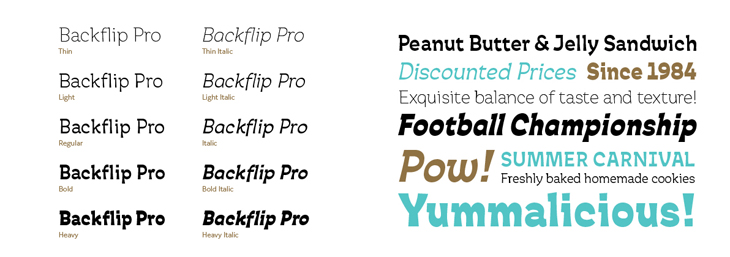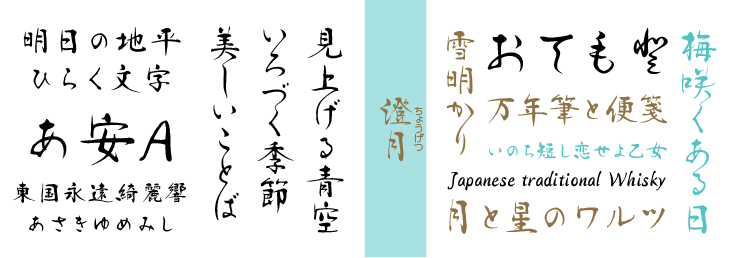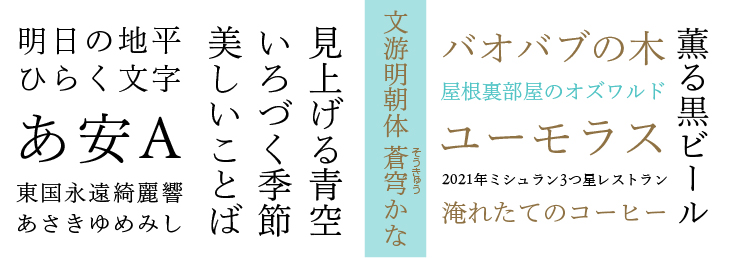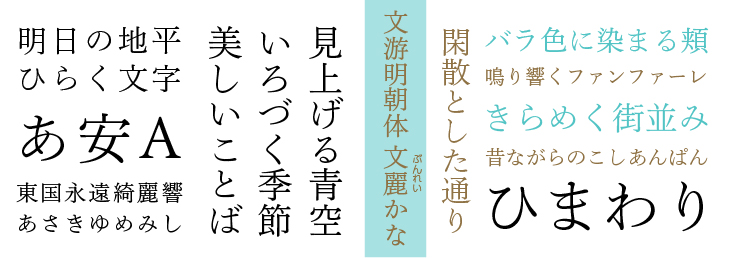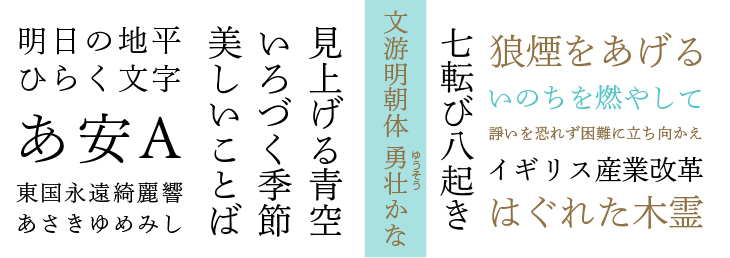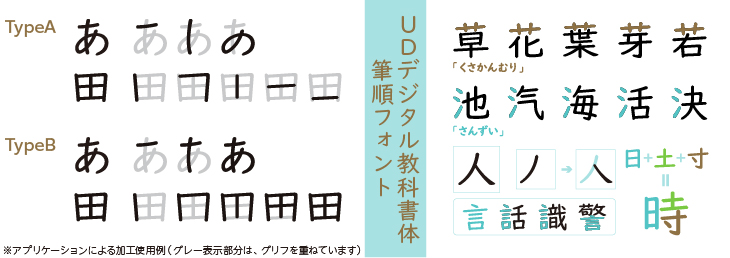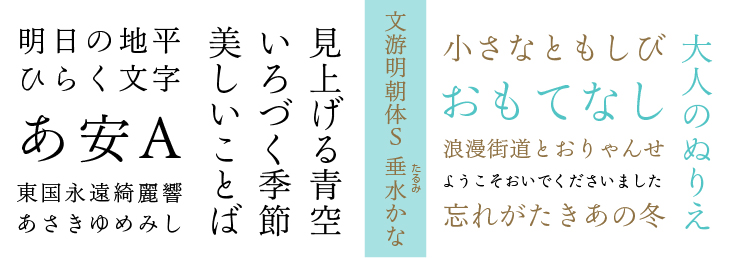
モリサワ2021年度新書体として、流れるように文字がつながる筆書体「澄月」など、デザインの幅を広げるラインナップを発表
モリサワは、2021年6月24日に2021年秋にリリースする新書体のラインナップを発表した。
2021年度は、モリサワのこれまでの技術力を結集することで、流れるように文字がつながる筆書体「澄月(ちょうげつ)」をはじめ、個性豊かな明朝体やゴシック体、ウエイト展開が豊富で利便性の高い欧文書体など、デザインの幅を広げるラインナップを提供することが発表された。
また、昨年に引き続き、人気和文書体にペアカーニングを搭載したAP版を加え、フォントの面から美しい組版を支えていく。
書家の筆遣いを感じる行書風デザイン書体「澄月」は、連綿体(つづけ字)や変体仮名などが搭載された書体。
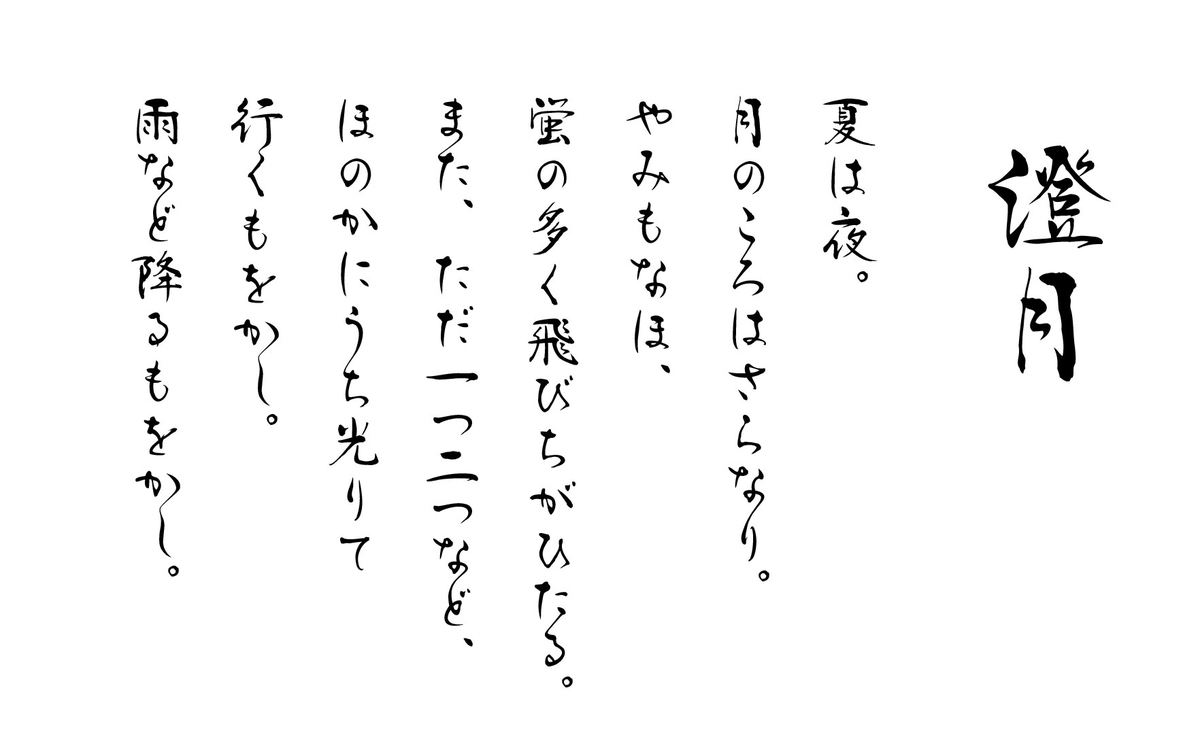
OpenType機能を活用することで、文脈に応じて字形が変化する仕組みになっていて、自然な手書き文字のニュアンスを演出する。
膨大な文字の組合せによって異なる字形を、書家やタイプデザイナー、エンジニアが協働して開発に取り組んだ。
また、クリーンな骨格に小さめの字面を持つゴシック体「あおとゴシック」や、中国の元王朝時代の注釈書と日本の元禄時代の浮世草子から復刻した筆脈を強く意識させる書体「げんろく志安(げんろくしあん)」、活版印刷のインクのにじみを再現したオールドスタイルの明朝体「秀英にじみ四号かな」、漢字の学習や教材作成に便利な「UDデジタル教科書体 筆順フォント」をリリースした。
欧文書体には、本格的な本文組版でも利用可能なヒューマニストサンセリフ「Sharoa Pro」や、軽快で遊び心のあるディスプレイ書体「Backflip Pro」が加わる。
グループ会社の字游工房からは、文学文藝作品を組むことを目的に制作された「文游明朝体」をはじめ、同書体と共通の漢字デザインをもつ別かなシリーズ「文麗かな」「蒼穹かな」「勇壮かな」「垂水かな」といった、本文組版の可能性を広げるラインナップを追加した。
さらに、今回の新書体追加にあわせて、「解ミン」、「フォーク」をはじめとした人気書体のAP版や、「秀英四号かな」を「秀英明朝」の漢字と合わせて総合書体化した「秀英四号かな+」も提供。
あおとゴシック
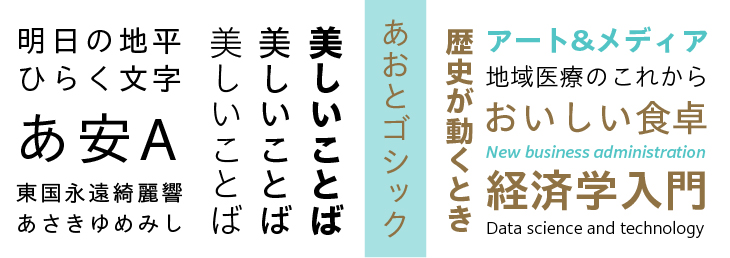
オンスクリーンでの本文利用を目的に開発されたゴシック体。
ややモダンなスタイルで、シンプルかつクリーンな骨格に、小さめの字面を採用することでUD書体などの従来のモダンゴシック体とは異なる表情の組版が可能になる。
なお本書体の欧文はSharoa Proをベースに作成され、イタリック体も搭載されている。
Sharoa Pro
明快なエレメントに、やや広めのカウンターを採用したヒューマニストサンセリフ。
10ウエイトで構成される豊富なウエイト展開と、スモールキャップや数字のバリエーションが搭載されており、本格的な本文組版にも対応可能。
なお本書体のデザインは、あおとゴシックの欧文エリアでも採用されており、同書体との併記利用にも最適となる。
澄月
繊細かつスピード感のある筆遣いの、行書風デザイン書体。
書家の筆遣いを忠実に再現するために、文字を入力するだけで文脈を考慮した連綿体などが自動で入力される仕組みを採用している。
そのほか、任意で選択入力可能な変体仮名などの異体字も搭載されている。
なお、本書体は全ての文字種が固有の字幅をもつプロポーショナル仕様となる。
げんろく志安
中国・元王朝の時代に福建地方で出版された注釈書『分類補註李太白詩』より復刻した漢字書体「志安」と、元禄時代に出版された浮世草子『世間胸算用』から復刻した和字(かな)書体「げんろく」を組み合わせた、筆の流れを強く意識させる書体。
活字として整備された中にも、起筆や収筆のうねるような筆脈の表現や、長体気味の文字形状から筆のニュアンスが感じられるため、他の書体にはない躍動感と威厳を醸し出し、目を引く効果を生む。
秀英にじみ四号かな
大日本印刷の金属活字「秀英四号明朝」を復刻したかな書体「秀英四号かな」をベースに、活版印刷による紙面上でのインクの滲みを再現した書体。
落ち着きのある端正なデザインのかなに「秀英にじみ明朝L」の漢字と欧文を合わせることで、本文組から見出しまで幅広い用途で使える、クラシックな印象の書体。
BackFlip Pro
軽快で遊び心のあるディスプレイ書体。
細いウエイトはオーガニックで優しい雰囲気、太いウエイトではフレアや、一般的な書体とは反対のコントラスト(抑揚)が強調されることで、ユニークな表情を演出。
製品パッケージや広告コピーなどの利用に最適。
UDデジタル教科書体 筆順フォント
学習指導要領に沿った字形「UDデジタル教科書体」を、書き順に沿ったストロークごとに一文字として、文字を書いていく過程を収録した書体。
書き順に沿って一画ずつバラバラに表示できる「TypeA」と、一画ずつ増やして表示できる「TypeB」の2タイプがある。
書体名に、小学生用は“E”、中学生用は“J”が付いている。
文游明朝体
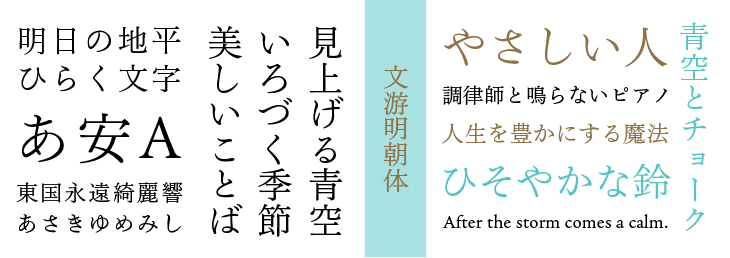
「時代をこえる普遍性を具えた造形美と可読性を標榜する日本の明朝体をつくる」をキーワードに開発された明朝体。
日本における文字の起源や歴史的背景をもとに、漢字・平仮名・片仮名それぞれが持つ固有の骨格を尊重した伝統的な字形が特徴。
単行本や文庫などの文学文藝作品において、美しく可読性の高い組版を実現した。
文游明朝体 文麗かな
「文游明朝体」の漢字に、近代文学を組むことを想定して制作された「文麗かな」を組み合わせた総合書体。
かなの線幅を太くすることで視認性を高めている。
やや扁平なデザインは本文組版で純文学の香り漂うクラシカルな雰囲気を演出。
文游明朝体 蒼穹かな
「文游明朝体」の漢字に、海外文学を組むことを目的として開発された「蒼穹かな」を組み合わせた総合書体。
簡潔なエレメントで構成されたデザインは澄み渡る青空をイメージしており、海外文学に多く出現する片仮名がやや大きく設計されていることが特徴。
本文組版で使用することで、文章を読みやすくクリアな印象に仕上げている。
文游明朝体 勇壮かな
「文游明朝体」の漢字に、プロレタリア文学をイメージして制作された「勇壮かな」を組み合わせた総合書体。
骨っぽく緊張感のある書風に加え、線幅がやや太く設計されていることで視認性の高い書体になっている。
本文組版で使用することで、クラシカルかつ力強い印象を与えることができる。
文游明朝体S 垂水かな
「文游明朝体」の字面を小さくした「文游明朝体S」の漢字に、縦方向への流れを意識して制作された「垂水かな」を組み合わせた総合書体。
小ぶりでやわらかな線質を持つかなは、鎌倉初期のスタイルを模範として制作された。
縦組みでの本文組版はもちろん見出しとしても利用することで、上品でつややかな雰囲気を演出。
〈総合書体化〉
秀英四号かな+